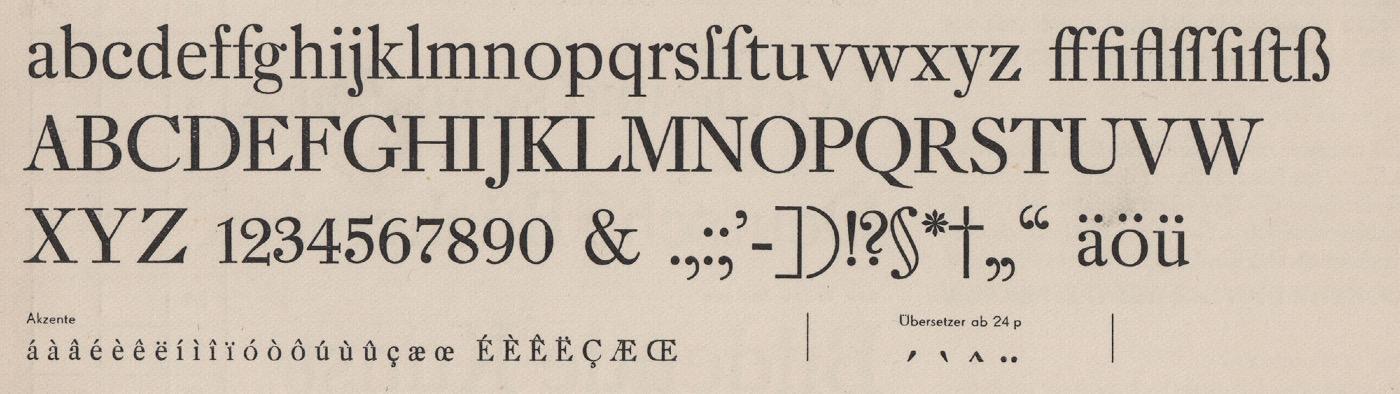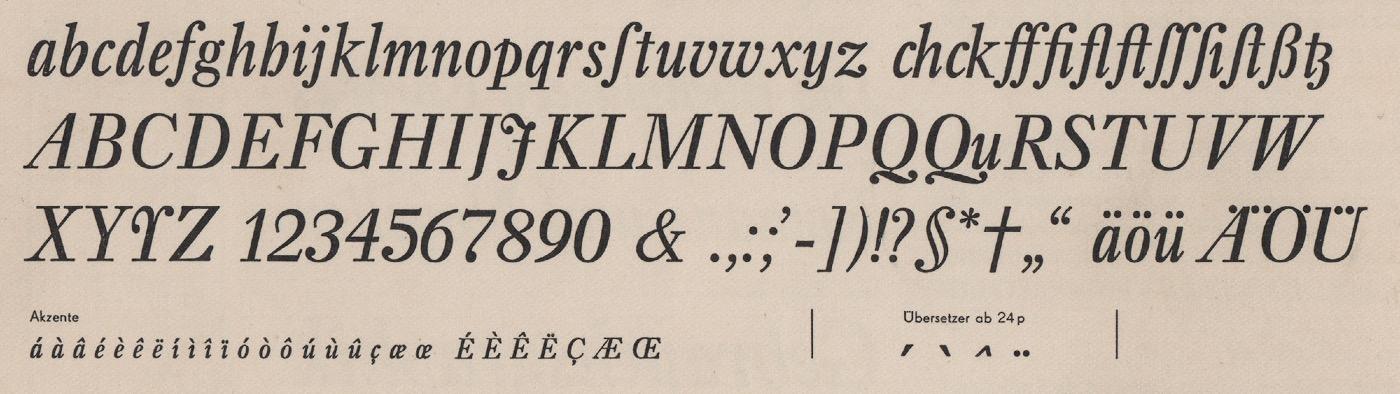
Font-Wiki: Fleischmann-Antiqua
Die Fleischmann-Antiqua ist ein Neuschnitt von Georg Belwe auf Basis der Fleischmann-Antiqua-Schriften aus dem 18. Jahrhundert. Die Schrift erschien in den 1920er-Jahren bei der Leipziger Gießerei Ludwig Wagner in drei Schnitten: mager, kursiv und halbfett. In der DDR war die Schrift über Typoart weiter erhältlich.